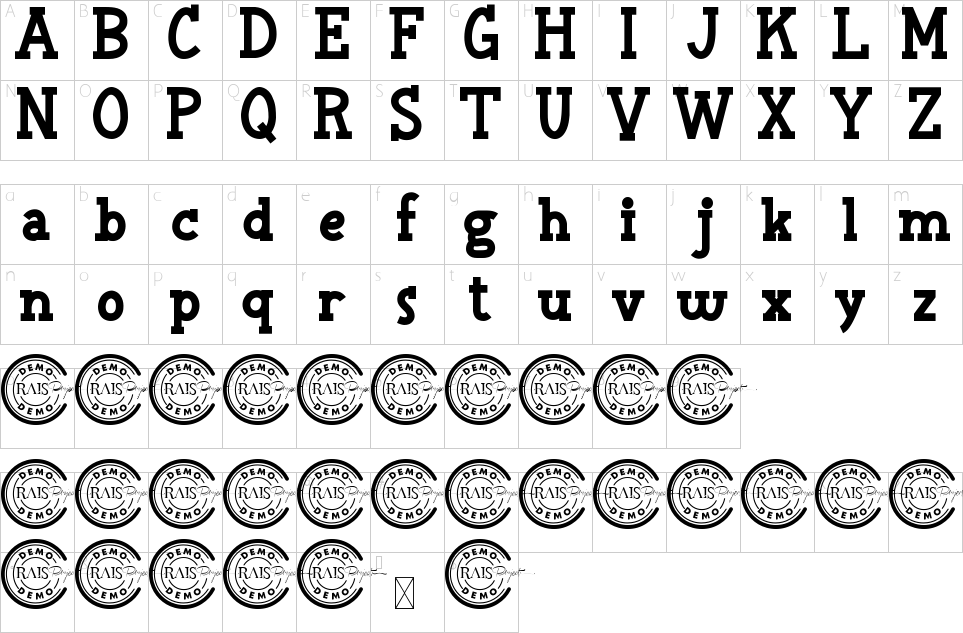
A fonte Adventure Land é um desfralde desconcertante para aqueles que estão em busca de uma escrita que seja tanto legal quanto o seu nome sugere. Desenvolvida pelo designer não informado, esta fonte oferece uma variedade de opções para decorar seus projetos com estilo. Com uma paleta vibrante e uma gama de estilos, Adventure Land é ideal para títulos e subtítulos, deixando seu texto brilhar em qualquer aplicação. Este design único foi baixado 2.886 vezes, evidenciando sua popularidade entre criadores de design. Se você busca uma fonte que é divertida, versátil e capaz de dar vida a seus projetos, Adventure Land pode ser a escolha perfeita para você. Engane-se, é uma fonte grátis, mas certamente não é menos interessante.